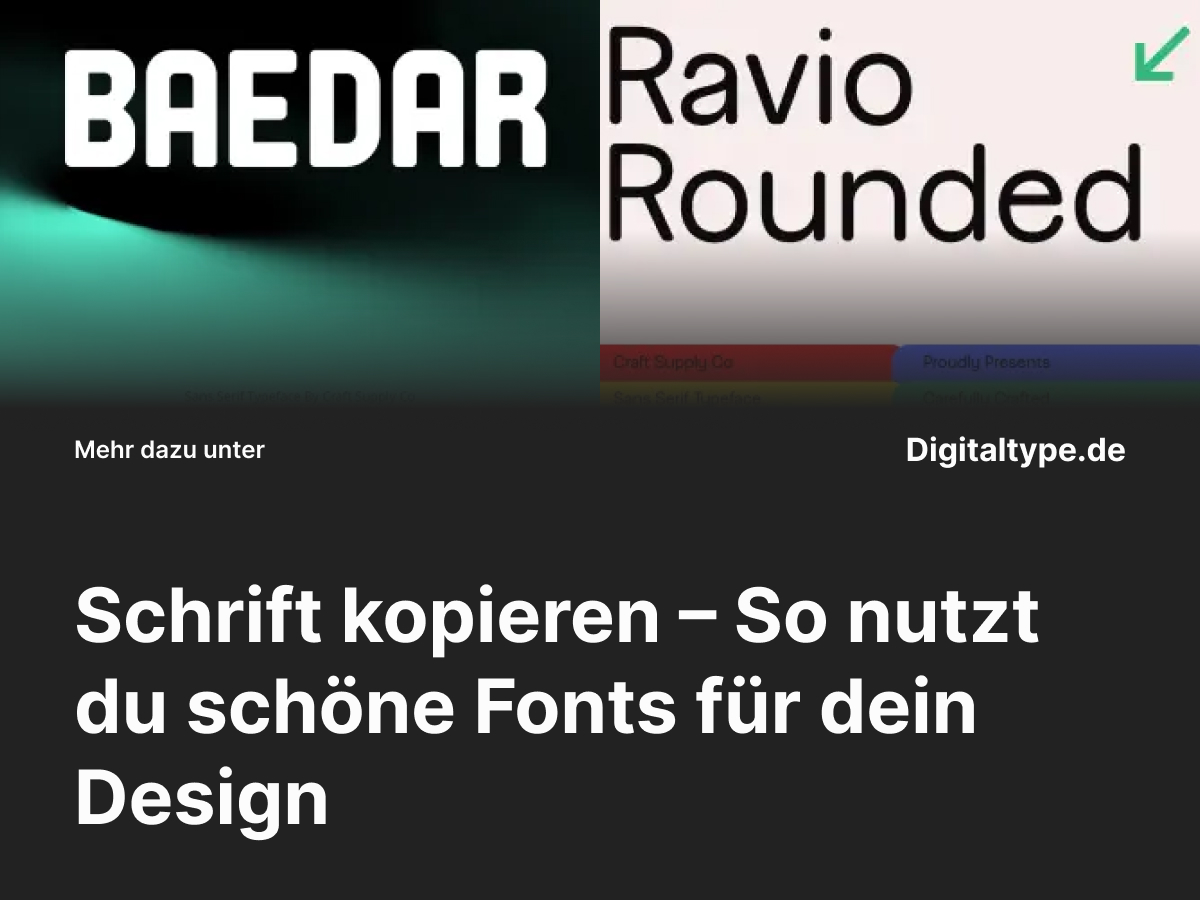
Schrift kopieren – So nutzt du schöne Fonts für dein Design
Du hast eine tolle Schrift gesehen und möchtest sie in deinem eigenen Design verwenden? Mit der richtigen Methode lässt sich jede Schrift kopieren und in dein Projekt integrieren.
Ob für Logos, Social Media oder Webseiten – kopierte Schriften können dein Design einzigartig machen, solange du sie richtig auswählst und einsetzt.
In diesem Artikel erfährst du, wie du Schriftarten sicher kopieren kannst und lernst sieben runde, moderne Fonts kennen, die du sofort für dein Branding oder kreative Designs verwenden kannst.
Was bedeutet „Schrift kopieren“?
Wenn man von Schrift kopieren spricht, meint man in der Regel das Übernehmen oder Verwenden eines bestimmten Schriftstils in anderen Anwendungen – etwa für Instagram-Bios, Webseiten oder Grafikdesigns.
Dazu gehören sowohl Online-Tools, mit denen du Schrift direkt kopieren und einfügen kannst, als auch der Einsatz von professionellen Fonts in Programmen wie Photoshop oder Canva.
Wann und warum du Schriften kopieren solltest
• 1. Für Social Media: Kopierte Schriften heben deine Posts, Bios oder Captions optisch hervor.
• 2. Für Branding: Einheitliche Schriften verleihen deinem Markenauftritt Professionalität.
• 3. Für kreative Projekte: Schriftkopien inspirieren neue Layouts und visuelle Ideen.
• 4. Für Präsentationen und Websites: Eine markante Schrift kann den Unterschied zwischen schlicht und beeindruckend ausmachen.
Die richtige Schrift zum Kopieren zu finden, ist der erste Schritt zu einem konsistenten, modernen Designstil.
Die 7 besten Schriftarten zum Kopieren für kreative Designs
Hier sind sieben hochwertige Fonts zum Kopieren, die mit ihren runden, modernen Formen sowohl freundlich als auch professionell wirken. Perfekt für Social Media, Branding und Webdesign.
1. Baedar Bold Rounded Sans Serif Font
Baedar ist ein kräftiger, runder Sans-Serif-Font mit moderner Anmutung. Ideal für Logos, Verpackungen und Social-Media-Designs, die Stärke und Freundlichkeit kombinieren.
2. Ravio Rounded Font
Ravio überzeugt mit sanften Kurven und ausgewogener Typografie. Perfekt für moderne Marken, UI-Designs und kreative Layouts.
3. Remond Rounded Drawn Font
Remond bringt einen handgezeichneten Charakter in deine Designs. Die runden Formen verleihen jedem Text Wärme und Persönlichkeit.
4. Radeil Rounded Rough Font
Radeil kombiniert abgenutzte Texturen mit sanften Rundungen – ideal für Vintage-Designs, Retro-Projekte oder organische Markenauftritte.
5. Qalited Rounded Font
Qalited ist eine moderne, leicht technische Schrift mit klaren Rundungen. Perfekt für Startups, Technologie-Designs und Marken mit modernem Image.
6. Radeil Rounded Drawn Font
Die handgezeichnete Variante von Radeil wirkt etwas weicher und natürlicher – ideal für kreative Marken, Lifestyle-Projekte und trendige Visuals.
7. Ranberg Rounded Drawn Font
Ranberg besticht durch seine einzigartige Mischung aus handgezeichneter Struktur und moderner Lesbarkeit. Ein vielseitiger Font für Editorials, Poster und Branding.
Design-Tipps für kopierte Schriften
• 2. Kombiniere runde und eckige Fonts: So erzeugst du interessante Kontraste im Design.
• 3. Achte auf Lesbarkeit: Besonders bei runden Schriften sollte Text auch in kleinen Größen klar erkennbar bleiben.
• 4. Halte dein Design konsistent: Nutze dieselbe Schriftfamilie für Branding und Online-Auftritte.
Fazit: Schrift kopieren für kreative Freiheit
Mit Schrift kopieren kannst du dein Design individuell gestalten und deinen Stil unterstreichen – ob für Social Media, Logos oder Webseiten.
Die hier vorgestellten runden Schriften bieten dir vielseitige Möglichkeiten, moderne und freundliche Layouts zu erstellen.
Wähle deinen Lieblingsfont, kopiere den Stil und bringe dein Design auf das nächste Level!